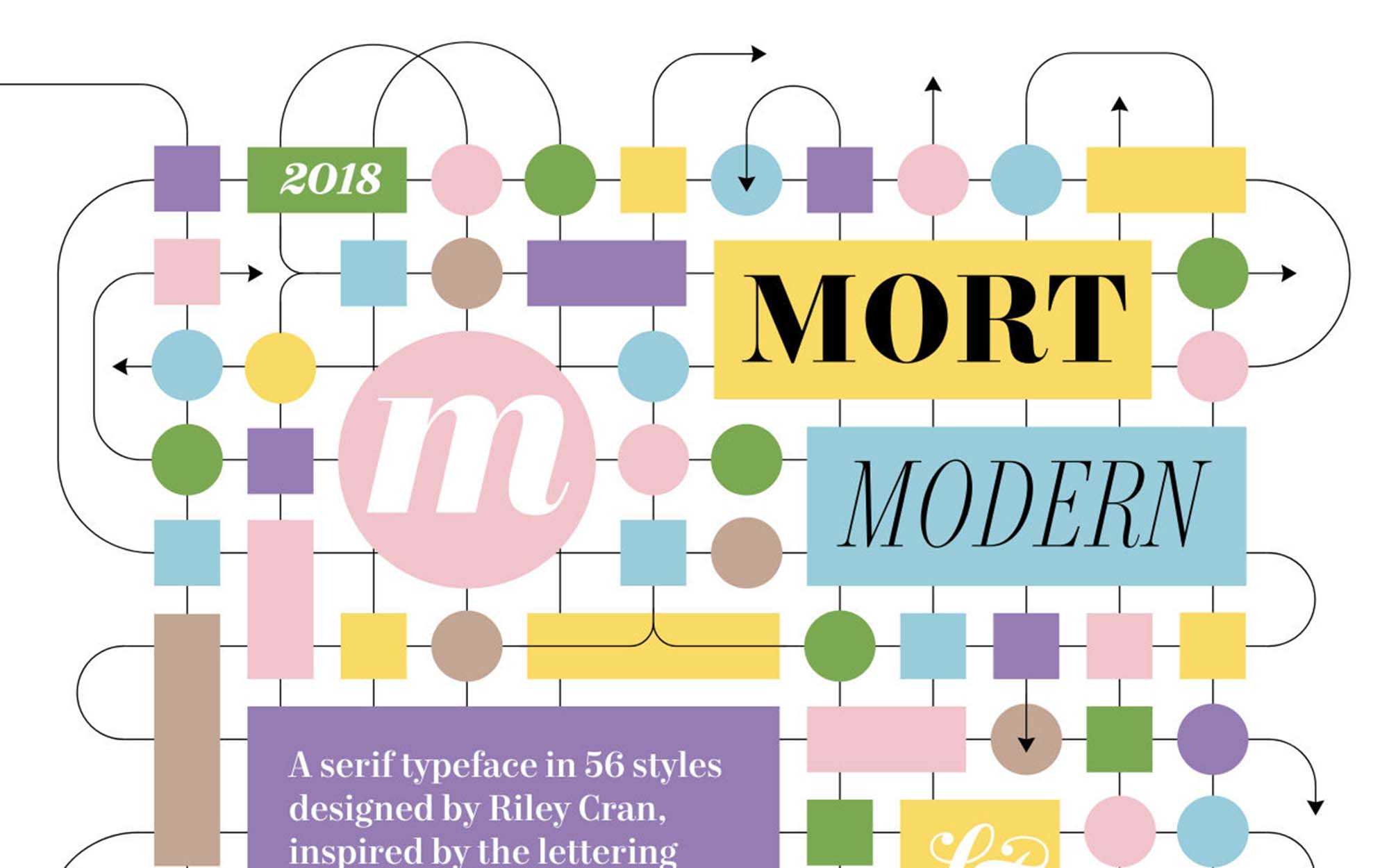
A fonte “Mort Modern” é um recurso gráfico de alta qualidade para mockups, criado para destacar a riqueza e diversidade das fontes modernas. Com seu design moderno e minimalista, essa fonte é perfeita para criar elementos gráficos em alta resolução. Ela também oferece a funcionalidade de expressar a individualidade e as personalidades únicas que cada fonte pode ter. Como mencionado na descrição original, esta fonte não apenas pode mostrar o visual de uma fonte, mas também a sua idade e o seu passado, permitindo que a represente de uma maneira que remete a um período específico, como o século XXI ou, na mesma medida, a um período histórico como a Idade da Prata. Portanto, “Mort Modern” é uma excelente escolha para quem procura um recurso que traz uma paixão histórica a uma estética futurista e moderna.